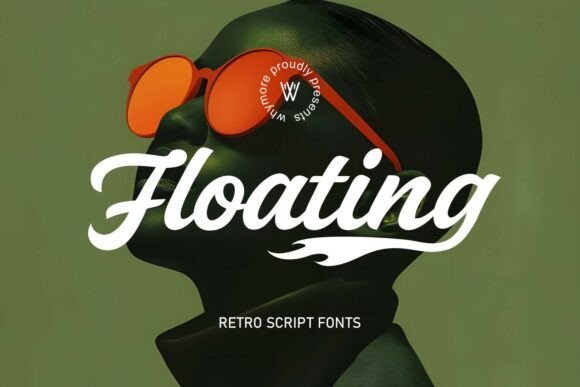
Floating Script
Việc tìm kiếm các thành phần thiết kế phù hợp có thể là một thách thức, nhưng Floating Script cung cấp một bộ sưu tập đặc biệt giúp nâng tầm công việc của bạn ngay lập tức.
Cho dù bạn đang tạo sản phẩm POD (In theo yêu cầu), thiệp mời đám cưới hay đồ họa mạng xã hội, Floating Script đều là một sự lựa chọn lý tưởng.